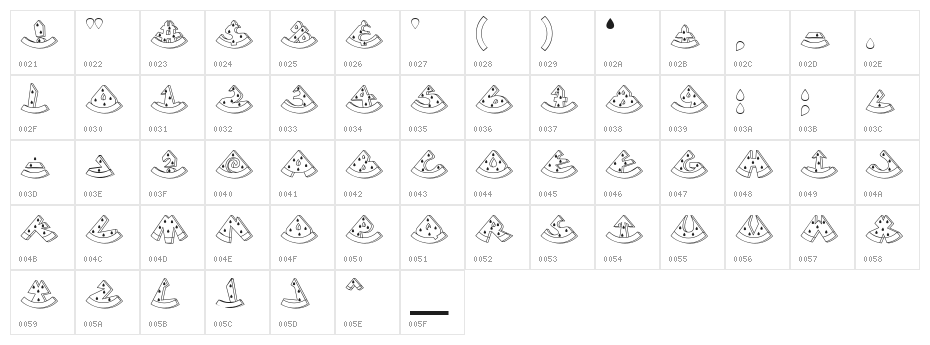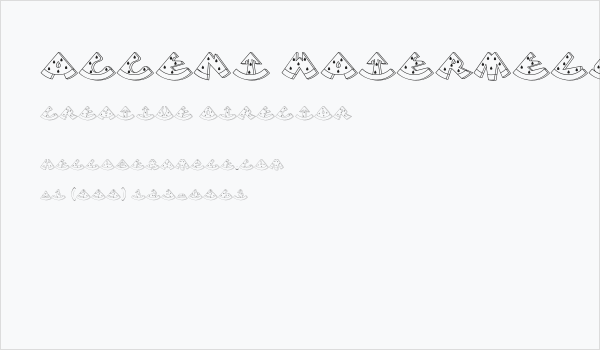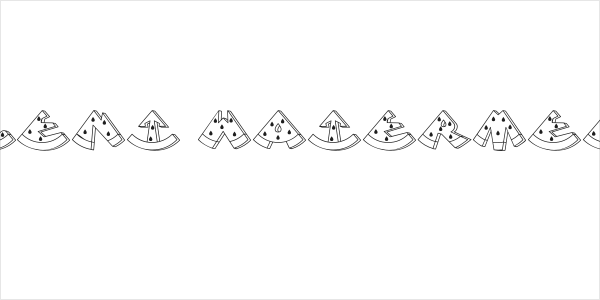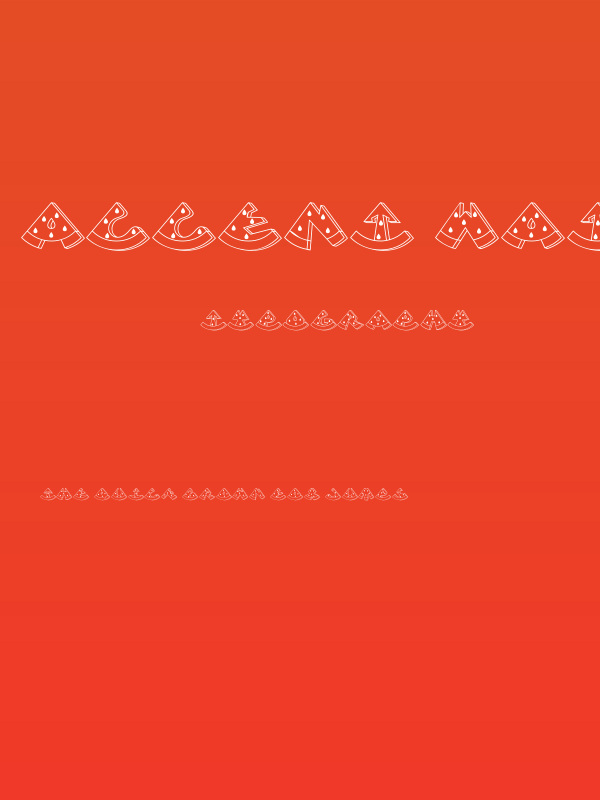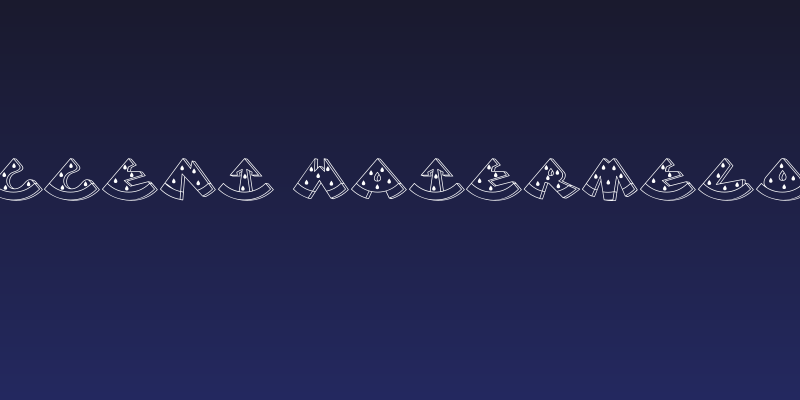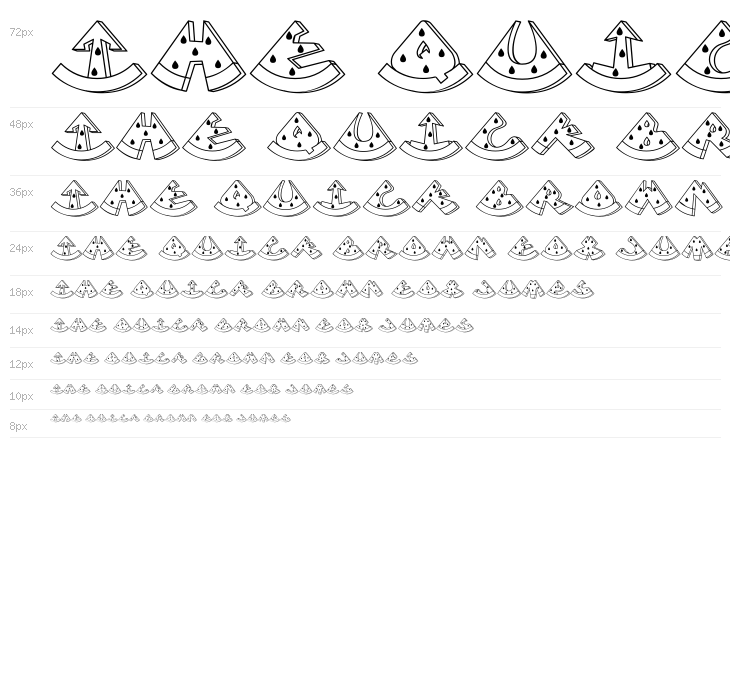
Accent Watermelon Font
| Progetti proposti | Ideal for summer event posters, children's party invitations, fruit-themed branding, or playful merchandise designs. |